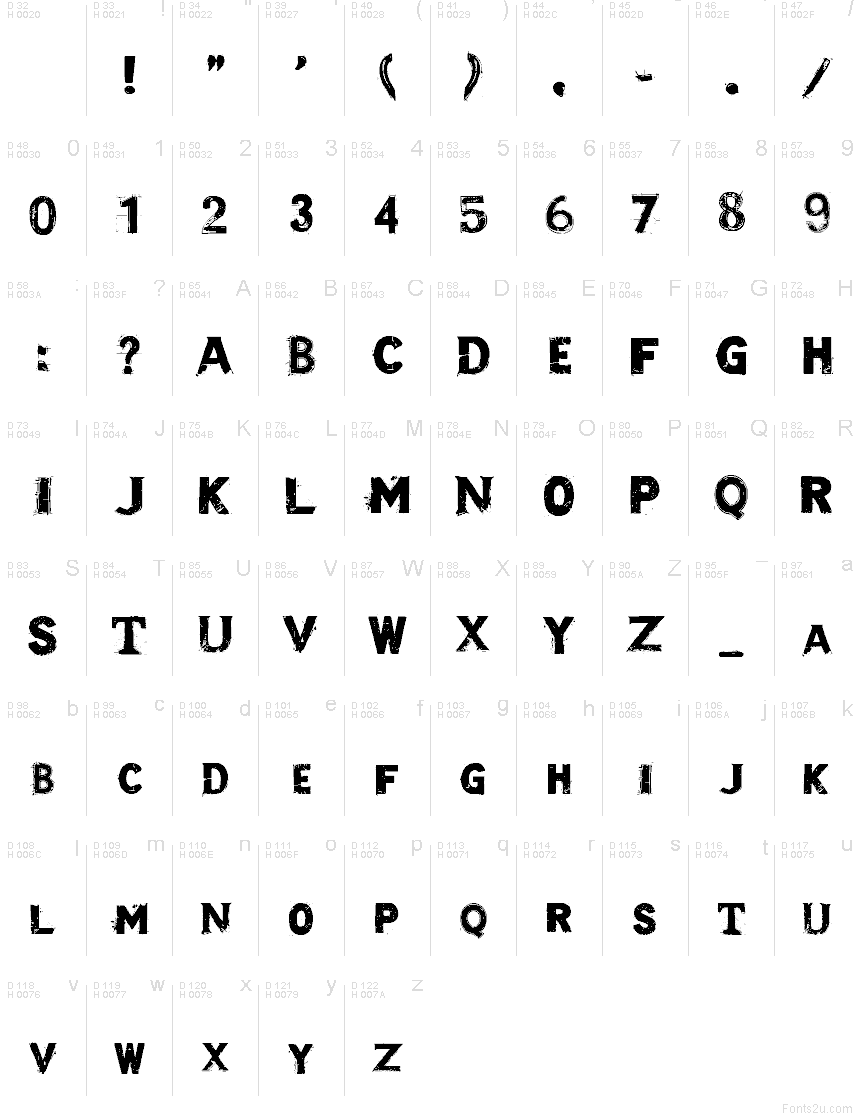
I've Got Rabies es una fuente de visualización erosionada y gratuita creada por Mike Larsson bajo el nombre MR.FISK, con formas de letras contundentes y pesadas, y una textura de impresión desgastada. Bordes irregulares, interiores socavados y motas esparcidas hacen que las letras parezcan tinta estampada sobre una superficie rugosa y dañada.
Un cartel de concierto punk es su entorno ideal, aunque sus formas desgastadas también se adaptan a portadas de álbumes, merchandising de skate y gráficos de eventos de terror. Su superficie raspada encaja con la música underground y las temáticas urbanas sucias.